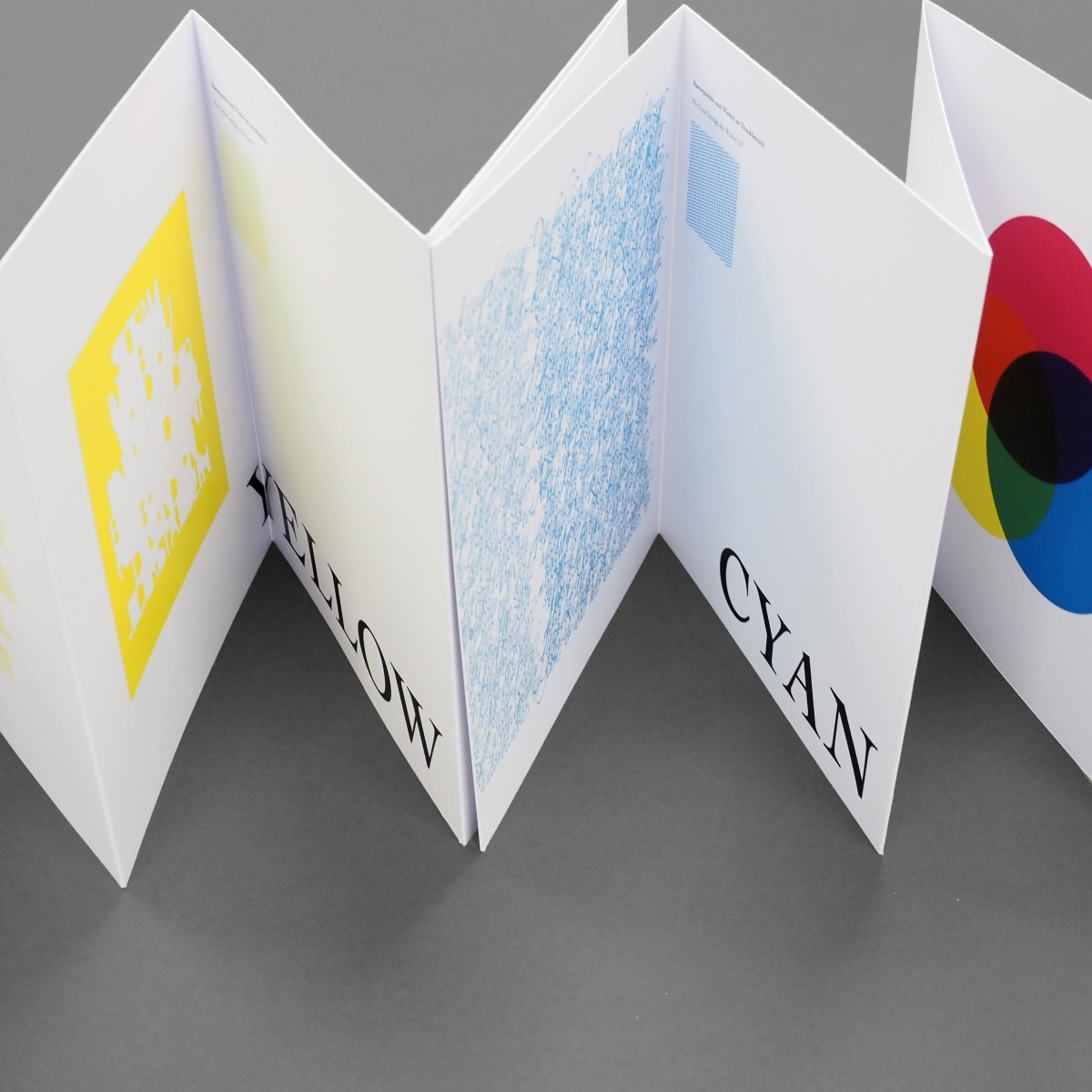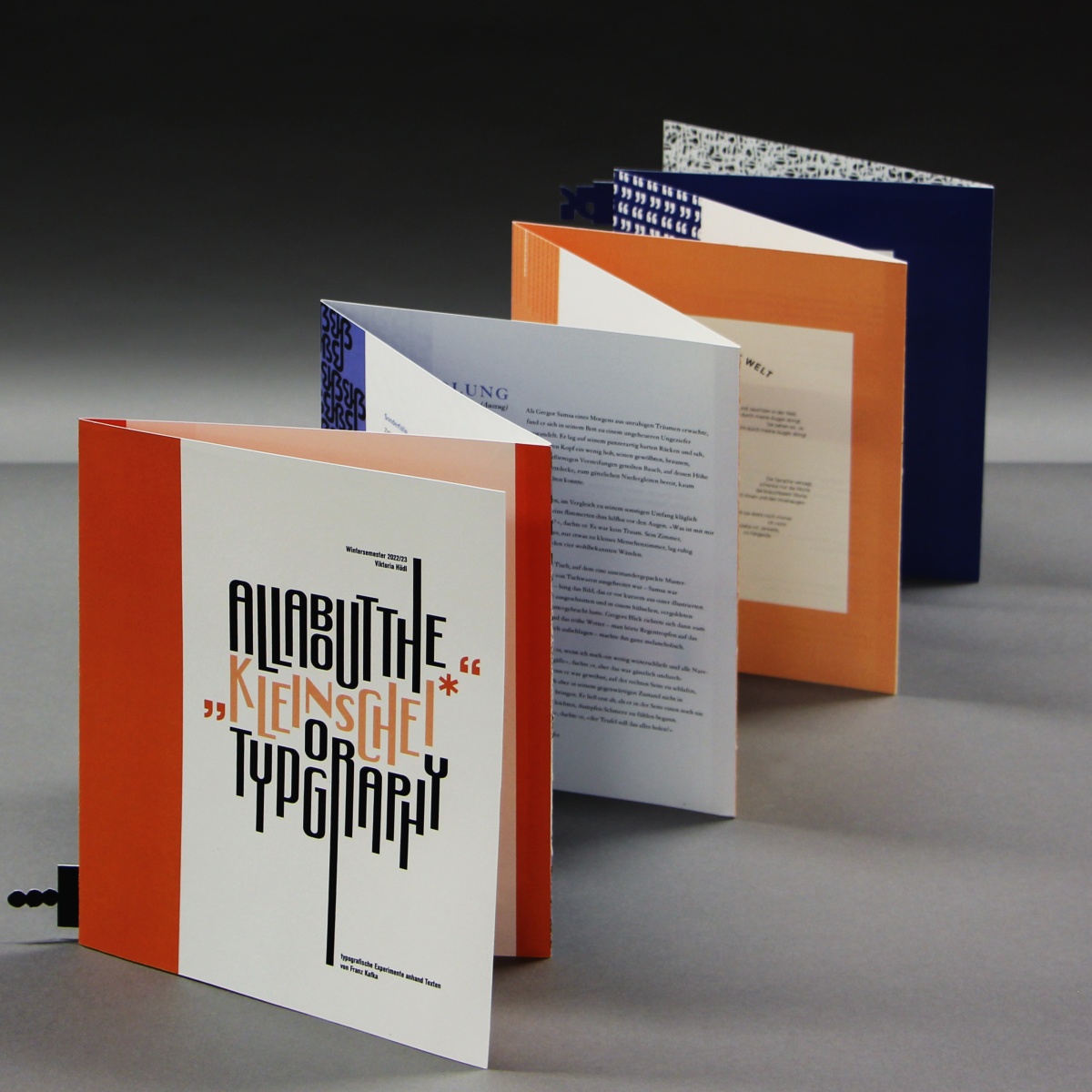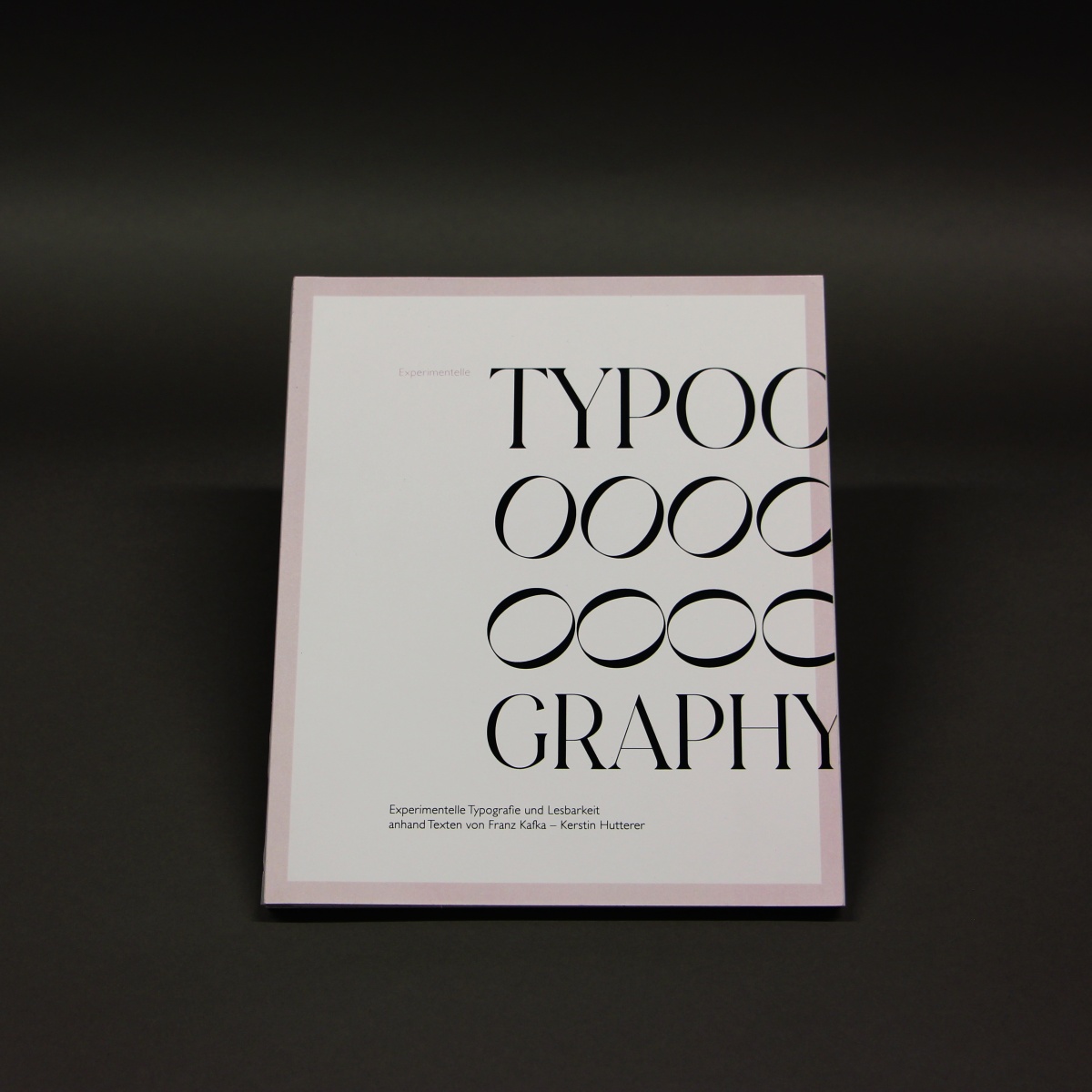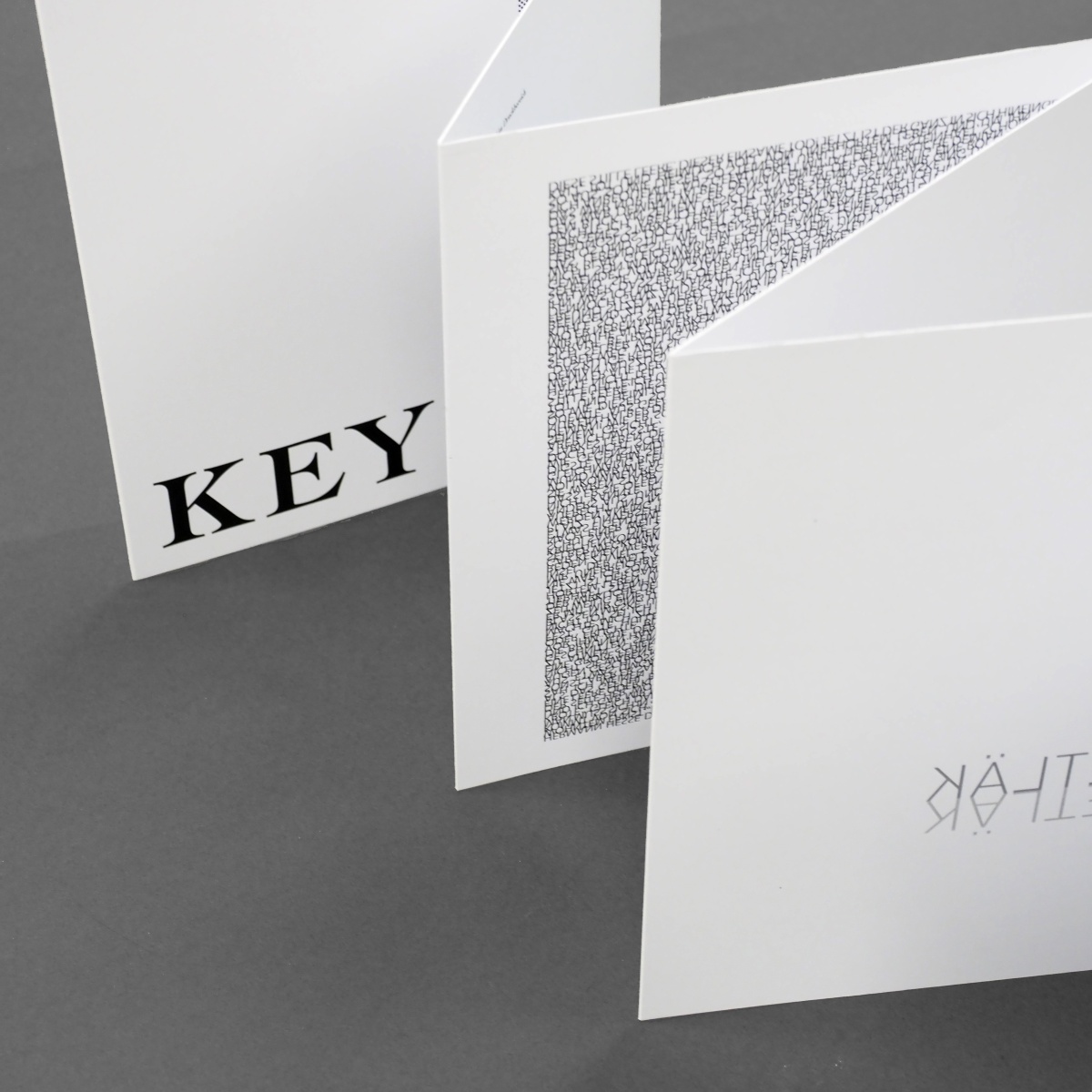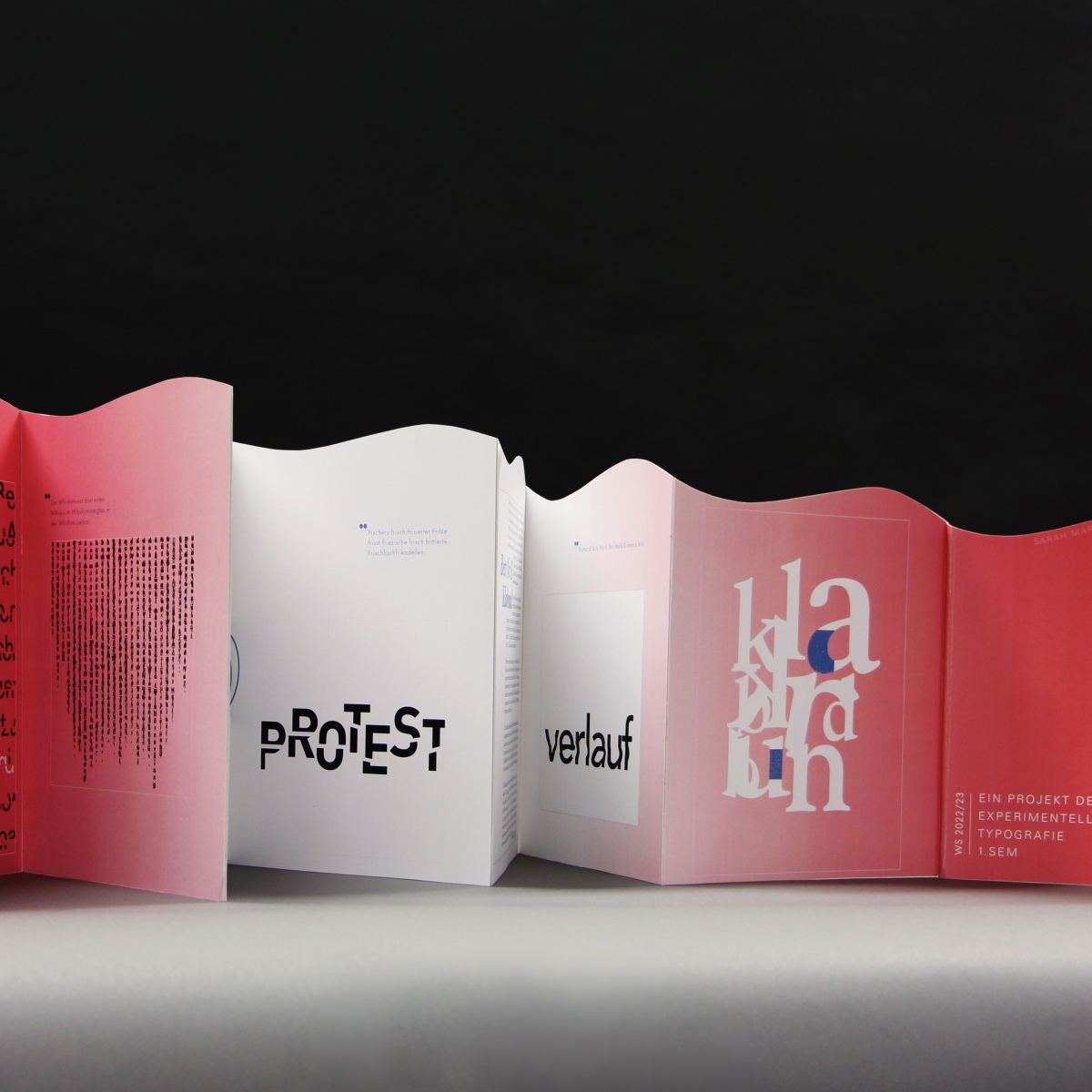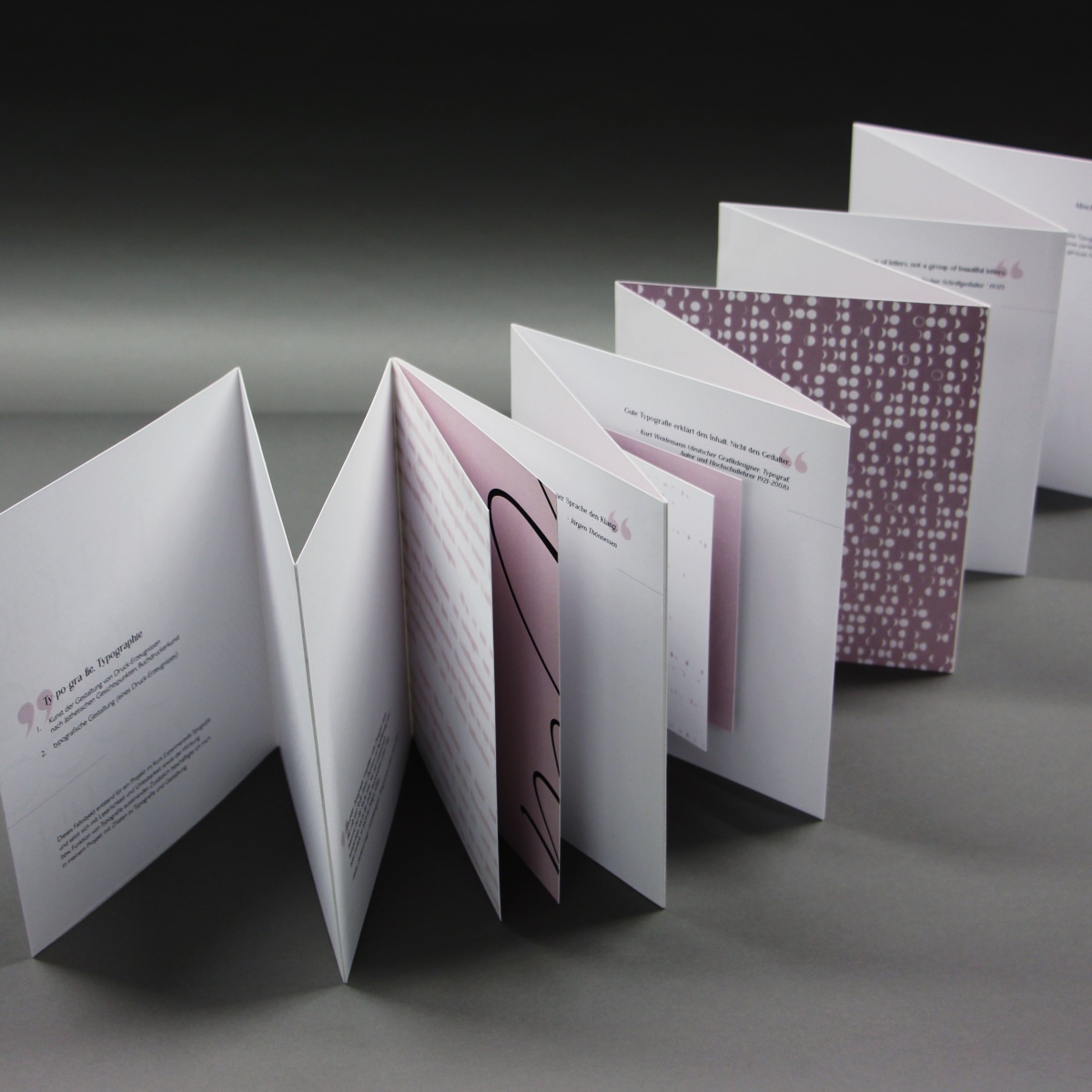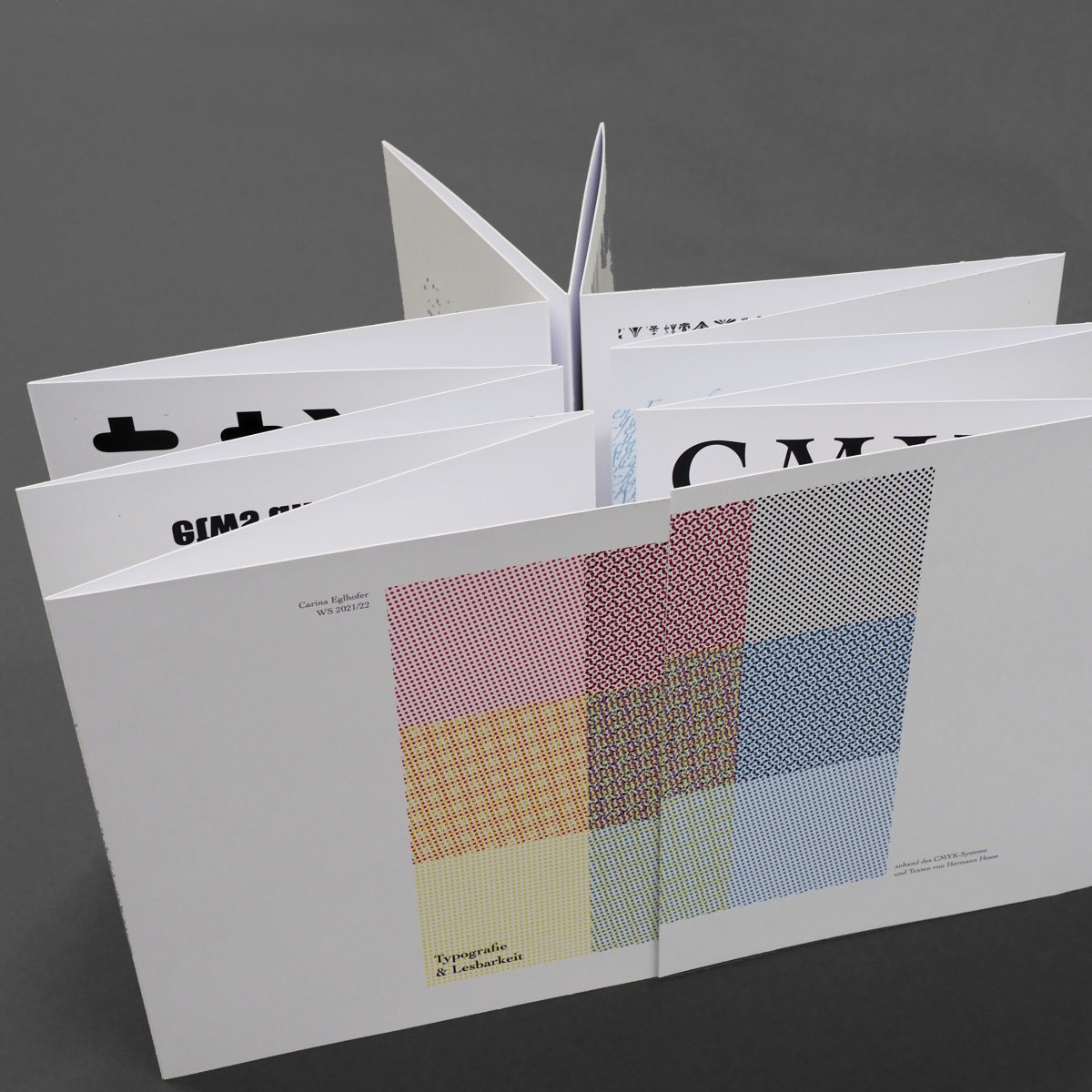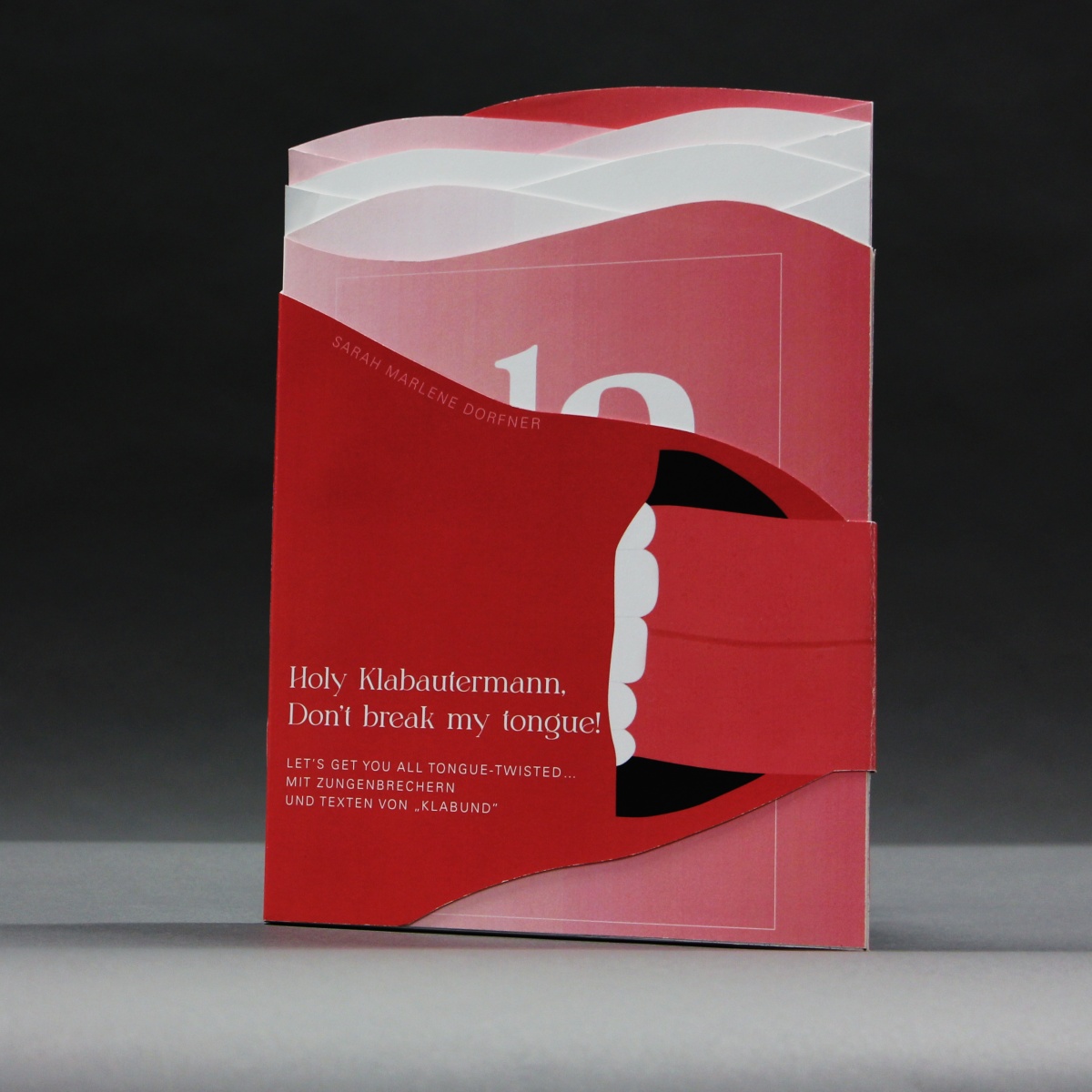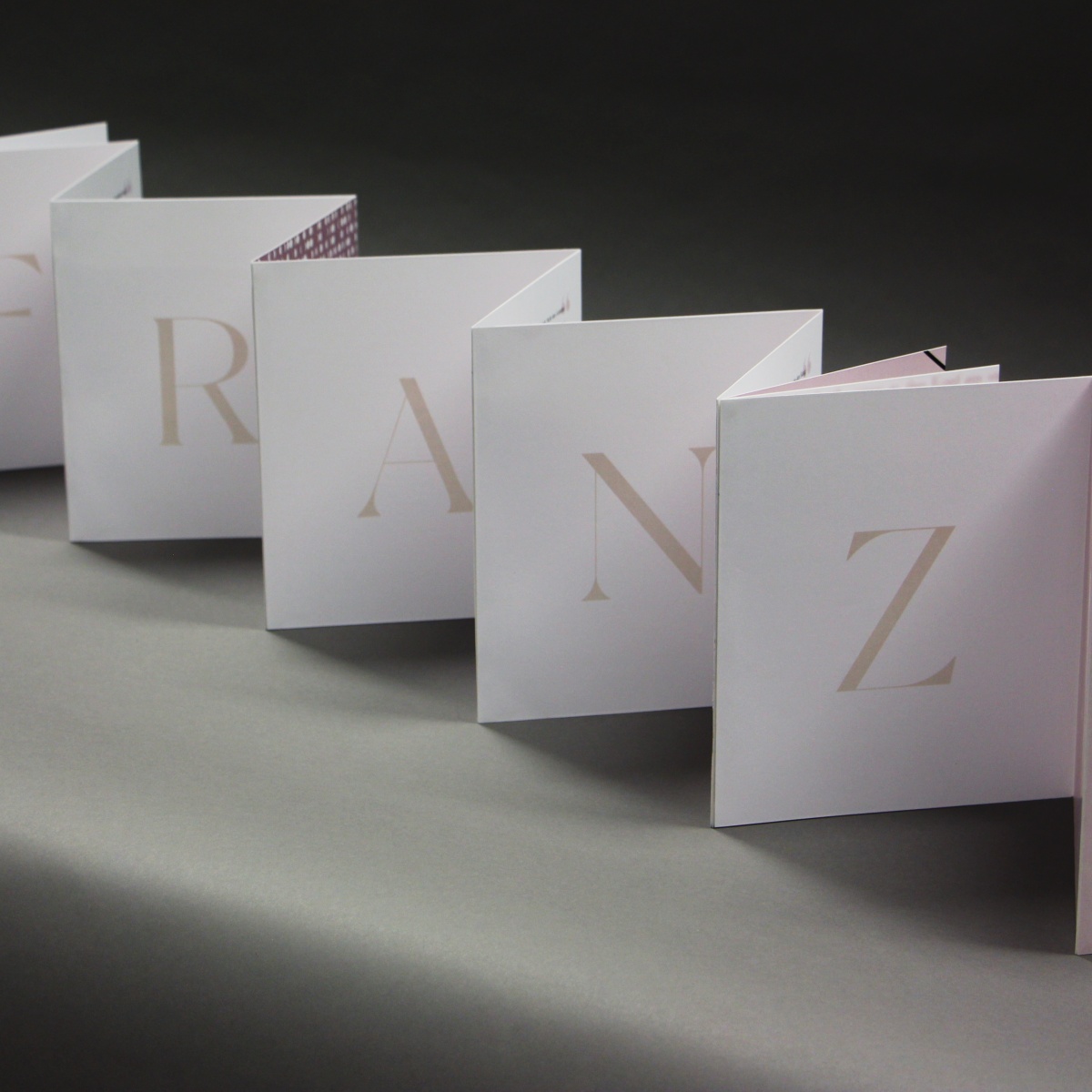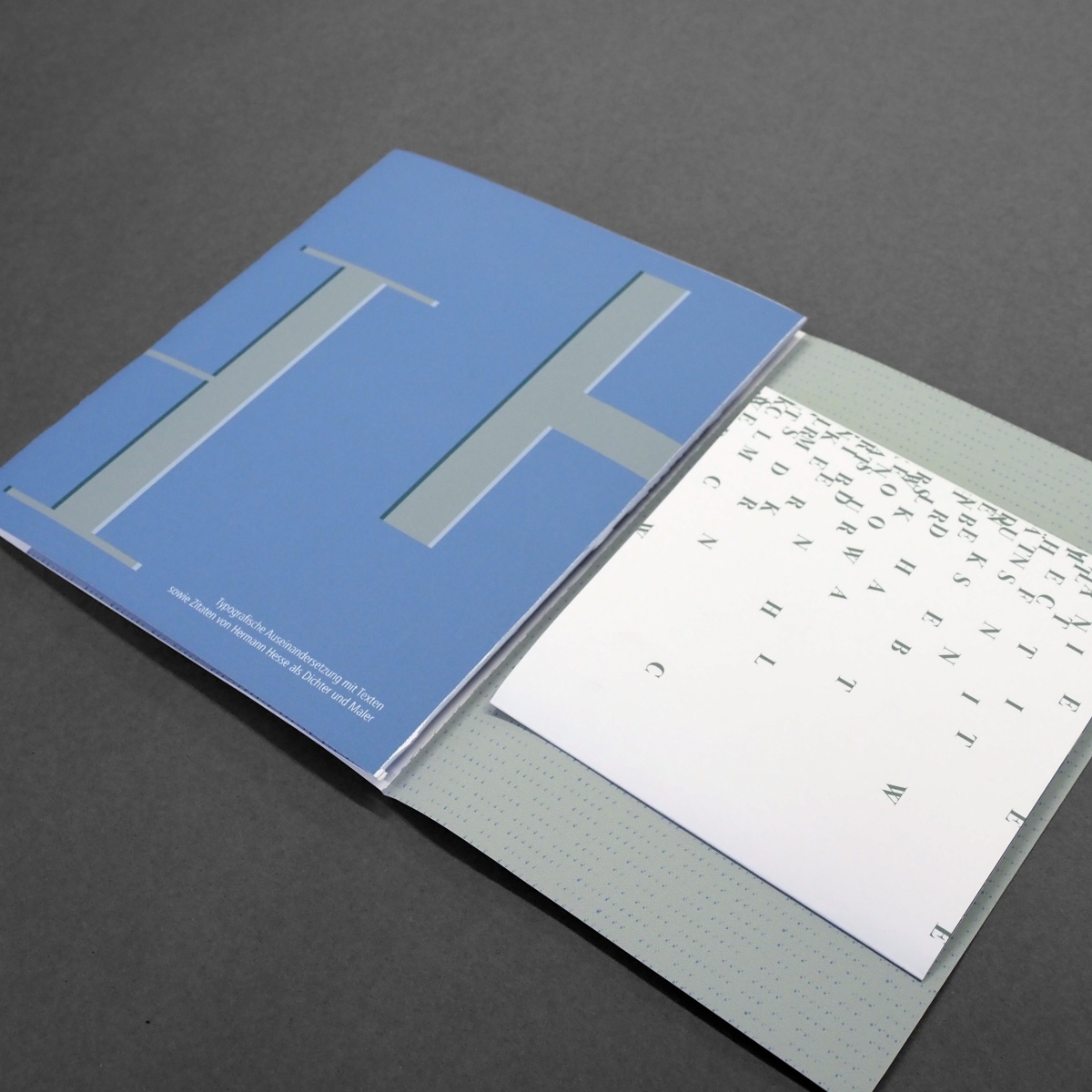
Experimentelle Typografie
Dieses Grundlagen-Projekt im ersten Semester dient dem spielerischen Erfahren und Erkennen der Regeln von Lesbarkeit und Leserlichkeit. Folgende Bereiche wurden innerhalb des Projektes bearbeitet:
Was muss beachtet werden, damit Lesetext einladend wirkt?
Wie schafft man durch Gliederung, Umbruch und Auszeichnung Hierarchien und einen angenehmen Textfluss, der das sinnhafte Erfassen von Text quasi unmerklich möglich macht?
Wo endet das Wahrnehmen von Schrift, wie kann man experimentell alleine mit Buchstaben gestalten?
Wie kann man ausschließlich mit Schrift ein Wort, eine Botschaft, so aussagekräftig wie möglich gestalten?
Welche Arten von Satzschriften gibt es, wie kann man diese klassifizieren?
Im Anschluss an diverse Übungen galt es, diese in einem Faltobjekt sinnvoll in Szene zu setzen.